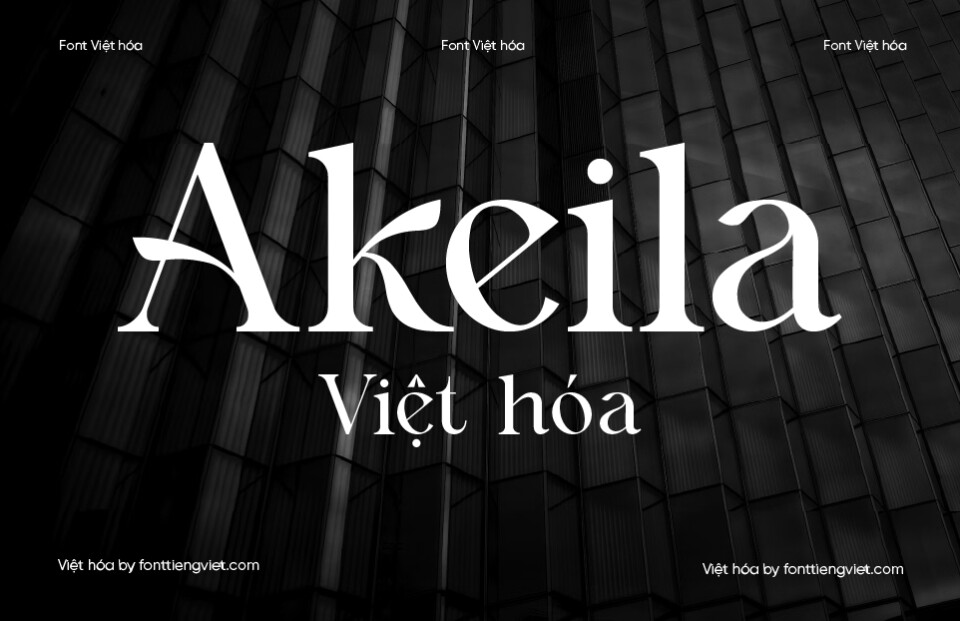
Font Việt hóa 1FTV VIP Akeila
Font Việt hóa 1FTV VIP Akeila – Bộ font sang trọng cho thiết kế chuyên nghiệp
Giới thiệu về Font Việt hóa 1FTV VIP Akeila
Trong thế giới thiết kế đồ họa hiện đại, việc lựa chọn một Font Miễn Phí chất lượng luôn là ưu tiên hàng đầu của các designer. Font Việt hóa 1FTV VIP Akeila nổi lên như một hiện tượng nhờ sự kết hợp hoàn mỹ giữa nét cổ điển và tinh thần hiện đại. Đây là bộ font thuộc phân khúc cao cấp, được tinh chỉnh kỹ lưỡng để phù hợp với bảng mã tiếng Việt, giúp người dùng không còn lo lắng về lỗi hiển thị dấu hay khoảng cách chữ không đều. Với cấu trúc thanh mảnh nhưng chắc chắn, Akeila mang lại cảm giác tinh tế, phù hợp cho nhiều loại hình dự án từ in ấn đến truyền thông kỹ thuật số.
Đặc điểm nổi bật của Font Việt hóa 1FTV VIP Akeila
Thiết kế Serif hiện đại và đẳng cấp
Font Việt hóa 1FTV VIP Akeila sở hữu những đường nét Serif (có chân) tinh xảo, tạo nên một diện mạo vô cùng chuyên nghiệp. Điểm đặc biệt của bộ chữ này chính là sự tương phản nhẹ nhàng giữa các nét thanh và nét đậm, giúp văn bản trở nên dễ đọc và có chiều sâu nghệ thuật. Khi áp dụng vào các tiêu đề lớn, bộ font này ngay lập tức thu hút thị giác và tạo ra một bầu không khí sang trọng cho toàn bộ tác phẩm thiết kế.
Tính ứng dụng linh hoạt trong giáo dục và sáng tạo
Dành cho các bạn học sinh, sinh viên và thầy cô giáo, Font Việt hóa 1FTV VIP Akeila là công cụ đắc lực để trang trí các slide bài giảng, làm bìa tiểu luận hay thiết kế thiệp mời sự kiện trường học. Sự rõ ràng của các ký tự giúp nội dung truyền tải mạch lạc, đồng thời thể hiện sự chỉn chu và tôn trọng đối với người xem. Không chỉ dừng lại ở đó, các nhà thiết kế còn sử dụng Akeila cho bộ nhận diện thương hiệu, logo các nhãn hàng thời trang hoặc bao bì sản phẩm cao cấp.
Cách tối ưu hóa Font Việt hóa 1FTV VIP Akeila trong thiết kế
Lựa chọn màu sắc và bố cục
Để Font Việt hóa 1FTV VIP Akeila phát huy tối đa vẻ đẹp, bạn nên kết hợp nó với những bảng màu tối giản như trắng, đen, vàng đồng hoặc các tông màu pastel trung tính. Về bố cục, hãy tạo ra các khoảng trắng rộng rãi xung quanh khối văn bản để các ký tự có không gian “thở”, giúp người xem cảm nhận được sự thoáng đãng và đẳng cấp mà bộ font này mang lại. Việc căn chỉnh lề giữa thường được ưu tiên khi sử dụng Akeila cho các trích dẫn hoặc tiêu đề trang bìa.
Kết hợp cùng các bộ font không chân
Một mẹo nhỏ trong thiết kế là hãy kết hợp Font Việt hóa 1FTV VIP Akeila với một bộ font Sans Serif (không chân) đơn giản cho phần nội dung chi tiết. Sự đối lập này không chỉ tạo ra nhịp điệu thị giác thú vị mà còn giúp phân cấp thông tin rõ ràng hơn. Điều này đặc biệt hữu ích khi trình bày các báo cáo khoa học hoặc tạp chí nghệ thuật, nơi yêu cầu sự cân bằng giữa tính thẩm mỹ và công năng sử dụng.
Kết luận về bộ font Akeila Việt hóa
Có thể khẳng định rằng, Font Việt hóa 1FTV VIP Akeila là sự lựa chọn không thể bỏ qua cho những ai đang tìm kiếm sự hoàn hảo trong từng nét chữ. Bộ font này không chỉ giải quyết bài toán về ngôn ngữ tiếng Việt mà còn nâng tầm giá trị thẩm mỹ cho mọi sản phẩm sáng tạo. Nếu bạn đang muốn làm mới phong cách thiết kế của mình, hãy trải nghiệm ngay Font Miễn Phí, Font Việt Hóa, Font Việt hóa 1FTV VIP Akeila để cảm nhận sự khác biệt vượt trội mà nó mang lại cho cộng đồng yêu nghệ thuật tại Việt Nam.